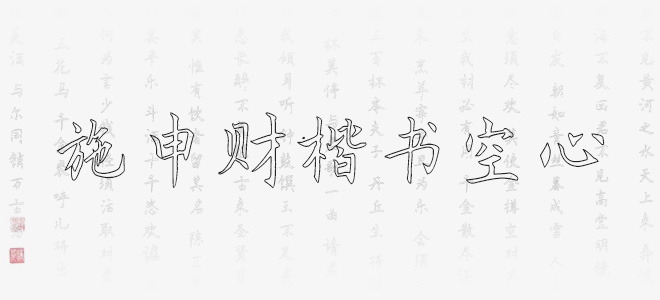
施申財(cái)楷書(shū)空心是一款賞心悅目、百看不厭的空心楷書(shū)字體,字體線(xiàn)條粗細(xì)適中,筆畫(huà)隨性,結(jié)構(gòu)肆意灑脫,具有很好的視覺(jué)感,適合于文化類(lèi)的宣傳設(shè)計(jì)、商業(yè)類(lèi)品牌的廣告和產(chǎn)品包裝設(shè)計(jì)以及個(gè)性化文字排版等較多場(chǎng)景。
施申財(cái)楷書(shū)空心